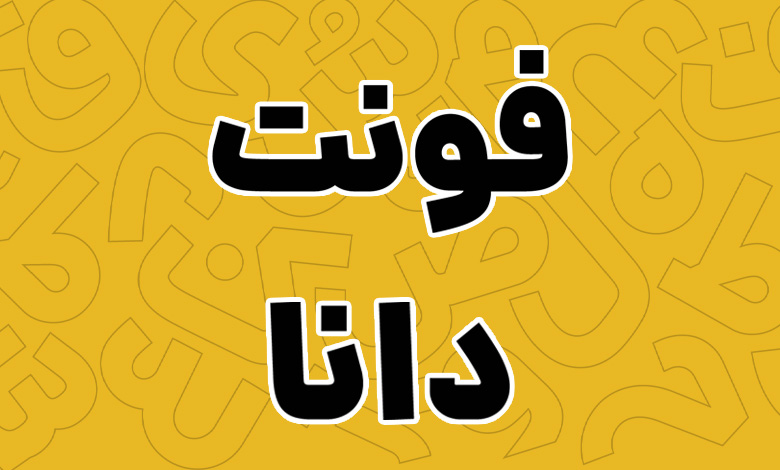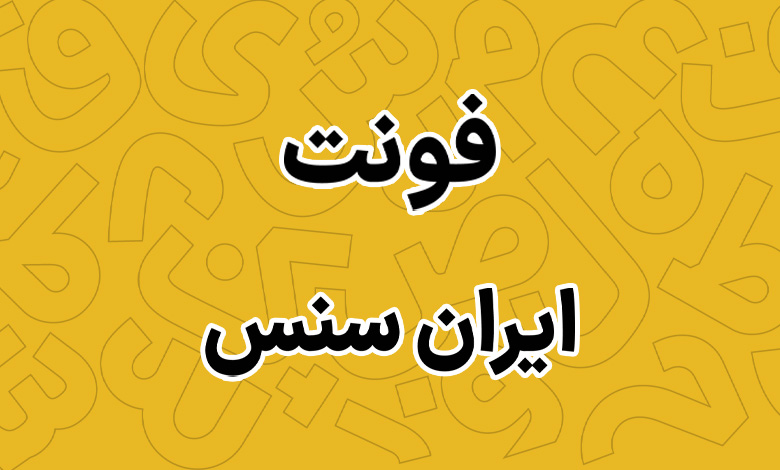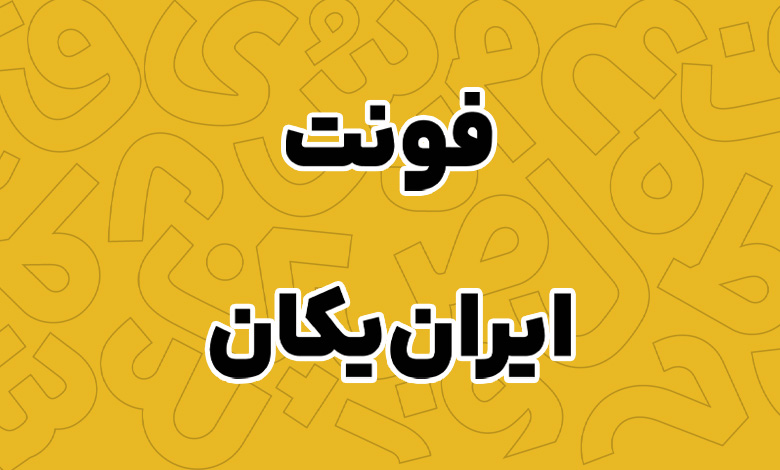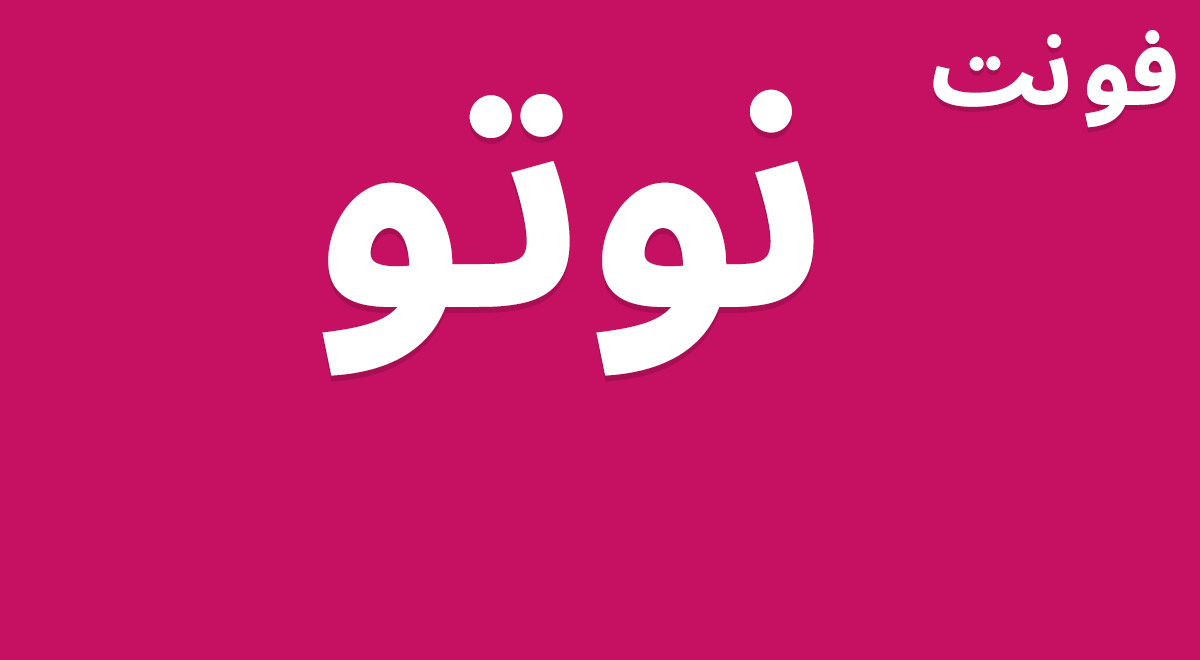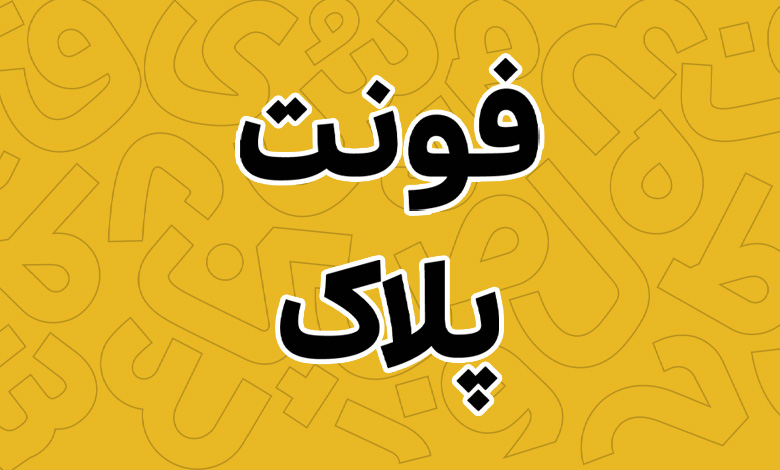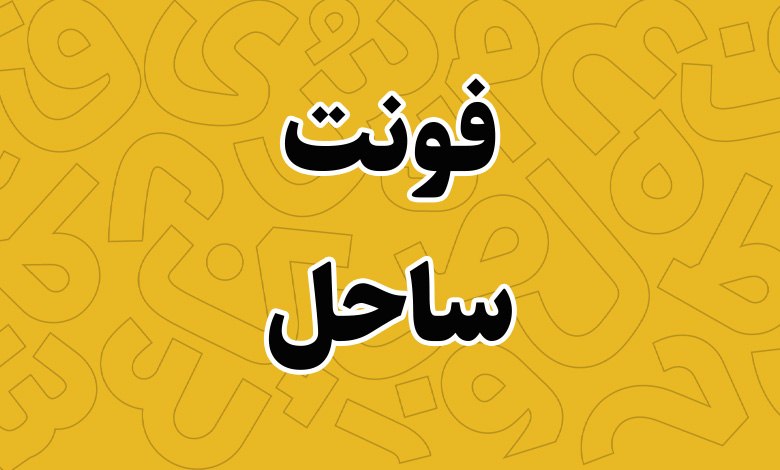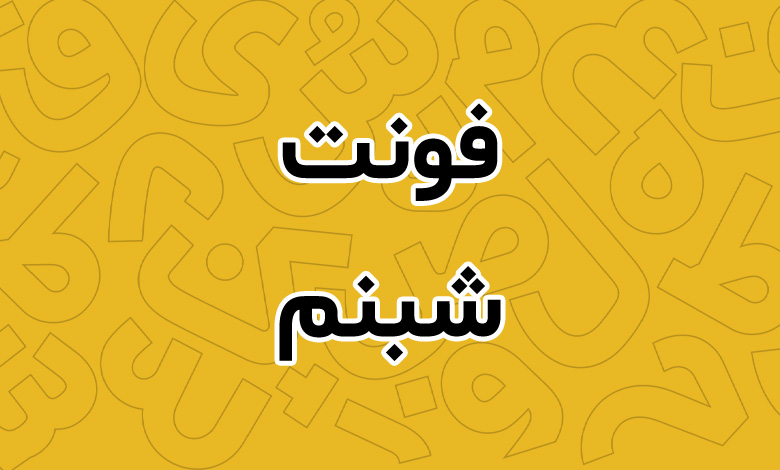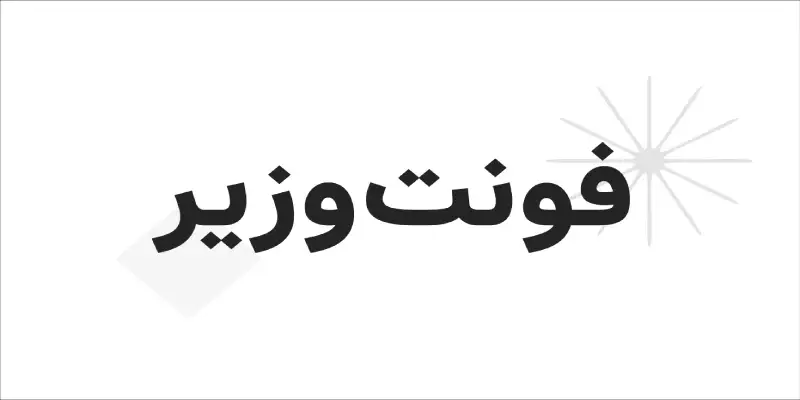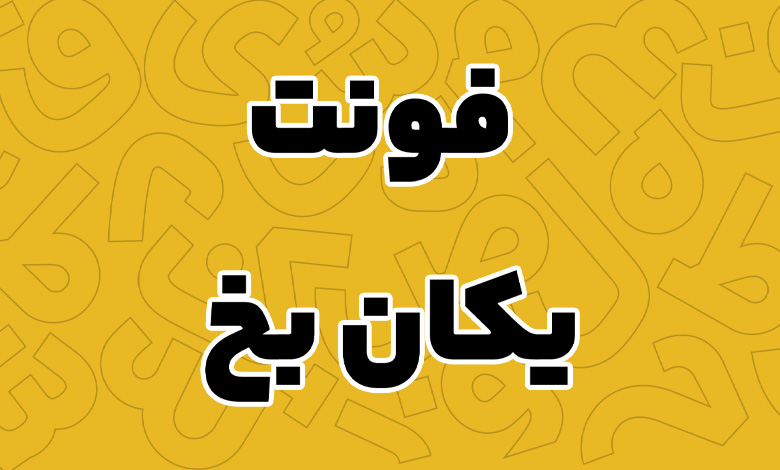
معرفی بهترین فونت های فارسی برای وب سایت
فونت های فارسی برای وب سایت
همانطور که فونت‌های انگلیسی جذابی برای طراحی سایت داریم، فونت‌های بسیار جذاب و کاربرپسندی نیز برای زبان فارسی وجود دارد که عموما افراد برای تایپوگرافی بهتر سایت فارسی خود به دنبال آن هستند. پیدا کردن بهترین فونت های فارسی برای طراحی سایت خود یک چالش برای افرادی است که بیش از پیش به طراحی و فونت‌های سایت خود اهمیت می‌دهند. در این مقاله قصد داریم بهترین گزینه‌ها را به شما معرفی کنیم.
معرفی بهترین فونت های فارسی برای طراحی سایت
برای طراحی یک وب‌سایت فارسی حرفه‌ای، جذاب و کاربرپسند، انتخاب فونت مناسب یکی از مهم‌ترین تصمیم‌هاست. فونت باید خوانا، زیبا و متناسب با هویت برند شما باشد. انتظار می‌رود که بهترین قالب های وردپرس از فونت‌های فارسی استاندارد استفاده کنند. در ادامه، برخی از بهترین فونت‌های فارسی برای طراحی سایت، شامل گزینه‌های رایگان و پرو را در ادامه مورد بررسی قرار می‌دهیم.
فونت های رایگان
فونت‌های رایگان به دلیل کیفیت بالا و در دسترس بودن، گزینه‌های فوق‌العاده‌ای برای پروژه‌های شخصی، استارتاپی و غیرتجاری هستند. این فونت‌ها به شرح زیر است:
۱. فونت وزیر – Vazir
وزیر، یکی از محبوب‌ترین و پرکاربردترین فونت‌های متن‌باز در جامعه وب فارسی است. این فونت توسط “صابر راستی‌کردار” طراحی شده و به دلیل سادگی، خوانایی بالا و انواع متعدد، برای استفاده در بسیاری وب‌سایت‌ها از مانند وب‌سایت‌های خبری و شرکتی مناسب است. طراحی ساده و هندسی، خوانایی عالی در اندازه‌های کوچک و بزرگ، پشتیبانی از وزن‌های مختلف، مناسب برای متن‌های طولانی از ویژگی‌های این فونت عالی است که عموما در انواع قالب رایگان وردپرس قابل مشاهده است.
فونت وزیر
۲. فونت شبنم – Shabnam
شبنم، فونتی با طراحی مدرن و نزدیک به فونت‌های پرمیوم مانند ایران‌سنس است. این فونت نیز توسط “صابر راستی‌کردار” طراحی شده و حسی دوستانه و صمیمی را به کاربر منتقل می‌کند. ویژگی‌های این فونت عبارت است از؛ طراحی روان و دلپذیر، خوانایی بالا، مناسب برای وب‌سایت‌های فروشگاهی، وبلاگ‌ها و پورتال‌های محتوایی.
فونت شبنم - Shabnam
۳. فونت ساحل – Sahel
ساحل یکی دیگر از فونت‌های رایگان با طراحی ساده و خوانا است که شباهت‌هایی به فونت‌های سنس‌سریف  انگلیسی دارد. این فونت برای پروژه‌هایی که به دنبال ظاهری مدرن و تمیز هستند، بسیار مناسب است. از ویژگی‌های بارز این فونت عبارت است از: ساختار هندسی و ساده، خوانایی خوب، مناسب برای متن و عناوین.
فونت ساحل - Sahel
۴. فونت یکان بخ – Yekan Bakh
یکان بخ، نسخه بهبود یافته و رایگان فونت یکان است که برای وب طراحی شده است. این فونت دارای ساختاری محکم و خوانا بوده و به خصوص برای عناوین و متن‌های اصلی در وب‌سایت‌های شرکتی و رسمی بسیار مناسب است. از ویژگی‌های این فونت عبارت است از: ساختار مستحکم و منظم، خوانایی بالا، ظاهری رسمی و حرفه‌ای.
فونت یکان بخ - Yekan Bakh
۵. فونت نوتو – Noto Sans Arabic UI
فونت نوتو، پروژه‌ای از شرکت گوگل است که با هدف از بین بردن مربع‌های خالی در زبان‌های مختلف طراحی شده است. نسخه عربی و فارسی این فونت با عنوان Noto Sans Arabic UI یک فونت متن‌باز و با کیفیت برای وب‌سایت‌های محتوامحور است. از ویژگی‌های بارز این فونت عبارت است از پشتیبانی از طیف گسترده‌ای از کاراکترها، طراحی مینیمال و تمیز، سازگاری با استانداردهای وب.
فونت نوتو - Noto Sans Arabic UI
فونت‌های پرمیوم
این فونت‌ها توسط طراحان حرفه‌ای ساخته شده و با پرداخت هزینه لایسنس، می‌توانید از آن‌ها در پروژه‌های تجاری خود استفاده کنید. این فونت‌ها معمولا کیفیت بالاتر، تنوع وزن بیشتر و پشتیبانی بهتری دارند و معمولا در کسب و کارهایی که می‌خواهند برند باشند، فوق‌العاده‌ است.
۱. فونت ایران سنس – Iran Sans
ایران سنس را می‌توان پرچمدار فونت‌های مدرن فارسی دانست. این فونت که توسط “مسلم ابراهیمی” طراحی شده، انقلابی در تایپوگرافی وب فارسی ایجاد کرد. ظاهر ساده، خوانایی بی‌نظیر و تنوع وزنی بالا، آن را به انتخاب اول بسیاری از برندهای بزرگ تبدیل کرده است. از ویژگی‌های مهم این فونت عبارت است از طراحی هندسی و مینیمال، خوانایی فوق‌العاده در انواع دستگاه‌ها و اندازه‌ها، بیش از ۱۰ وزن مختلف از بسیار نازک تا بسیار بولد، حسی مدرن و قابل اعتماد.
فونت ایران سنس - Iran Sans
۲. فونت ایران یکان – Iran Yekan
ایران یکان که توسط همان طراح فونت ایران سنس طراحی شده، ظاهری کمی متفاوت و منحصر به فرد دارد. این فونت با ساختاری شکیل و هندسی، برای وب‌سایت‌هایی که به دنبال تمایز و هویت بصری قوی هستند، ایده‌آل است. از ویژگی‌های بارز این فونت عبارت است از ظاهری شیک و رسمی، خوانایی بسیار خوب، مناسب برای عناوین و متن‌های اصلی، پشتیبانی از وزن‌های متعدد.
فونت ایران یکان - Iran Yekan
۳. فونت دانا – Dana
دانا، یکی از فونت‌های جدید و بسیار محبوب است که با طراحی خاص و متفاوت خود، جایگاه ویژه‌ای در میان طراحان پیدا کرده است. این فونت دارای انحناهای ملایم و ظاهری دلنشین است. ویژگی‌های بارز این فونت عبارت است از طراحی جذاب و منعطف، دارای ۱۰ وزن مختلف، مناسب برای وبلاگ‌های شخصی، وب‌سایت‌های مجلات و برندهای خلاق.
فونت دانا - Dana
۴. فونت کادر – Kadr
کادر، یک فونت هندسی و مدرن با ساختاری تمیز و منظم است. این فونت به دلیل خطوط صاف و زوایای دقیق، برای وب‌سایت‌های تکنولوژی‌محور و رابط‌های کاربری (UI/UX) بسیار مناسب است. از ویژگی‌های بارز این فونت عبارت است از طراحی مینیمال، ساختارمند و با زاویه‌های دقیق، مناسب برای عناوین و متن‌های کوتاه.